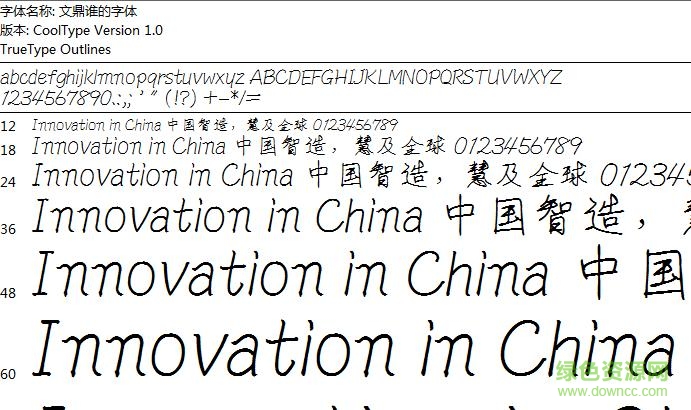
sheideeg medium gb
sheideeg medium gb字體是一款手寫(xiě)鋼筆字體,筆畫(huà)之間連筆較多,所以就會(huì)顯得特別的不一樣,有喜歡這類字體的朋友歡迎下載!
sheideeg medium gb字體簡(jiǎn)介
sheideeg medium gb字體就是文鼎誰(shuí)的字體,是文鼎字庫(kù)打造的一款手寫(xiě)字體,充分延續(xù)手寫(xiě)體的風(fēng)格,適合需要進(jìn)行藝術(shù)創(chuàng)作的朋友下載使用!
sheideeg medium gb字體